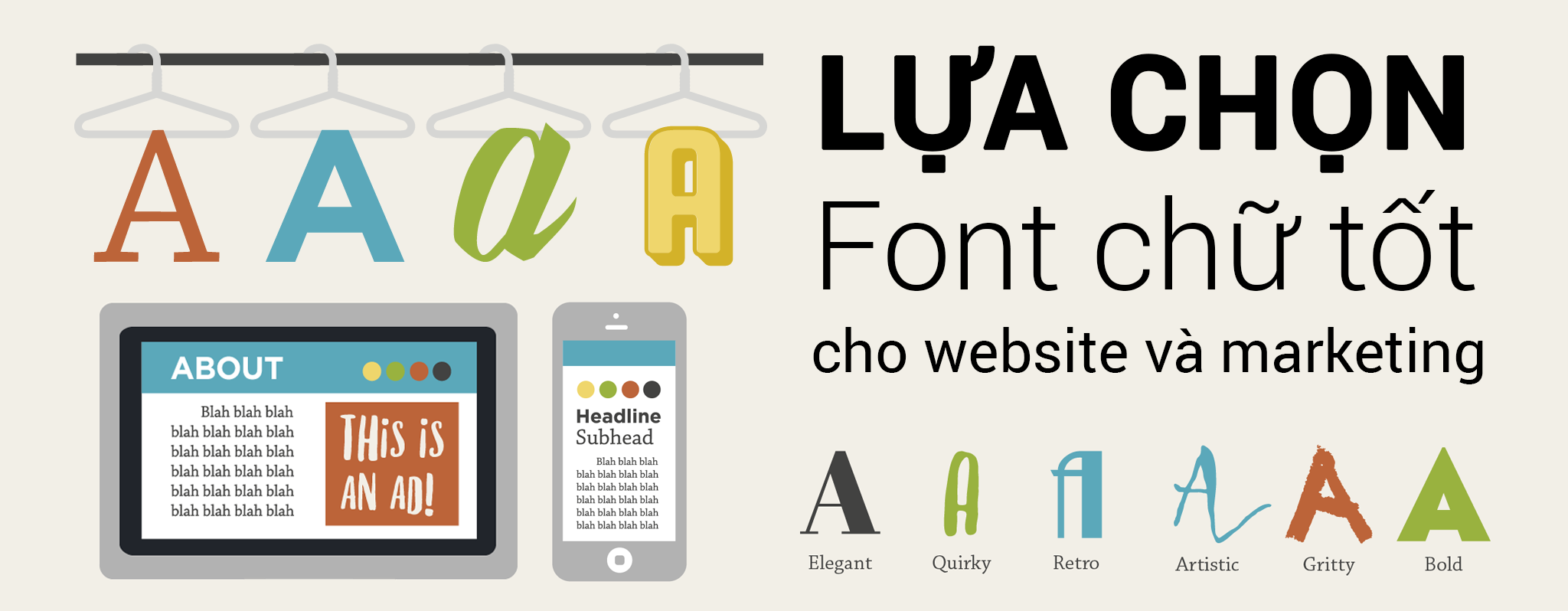
[Infographic] Lựa chọn Font chữ tốt cho website và marketing
Như các bạn đã biết, Font chữ được thể hiện dưới nhiều hình dạng và kích cỡ khác nhau. Giống như bộ trang phục vậy, nó có thể khơi gợi cảm xúc và hỗ trợ việc truyền đạt thông điệp một cách tốt hơn.
[Infographic] Lựa chọn Font chữ tốt cho website và marketing
Phong cách độc đáo khi thiết kế Font chữ là điều tốt nhưng bạn cũng phải quan tâm đến nhiều yếu tố khác nữa, vì nếu lựa chọn Font không phù hợp thì thông điệp mà bạn muốn truyền tải có thể bị bóp méo. Infographic sau đây sẽ cho chúng ta có cái nhìn sơ lược và cách chọn những loại Font phù hợp trong việc xây dựng website và marketing, mời các bạn theo dõi!